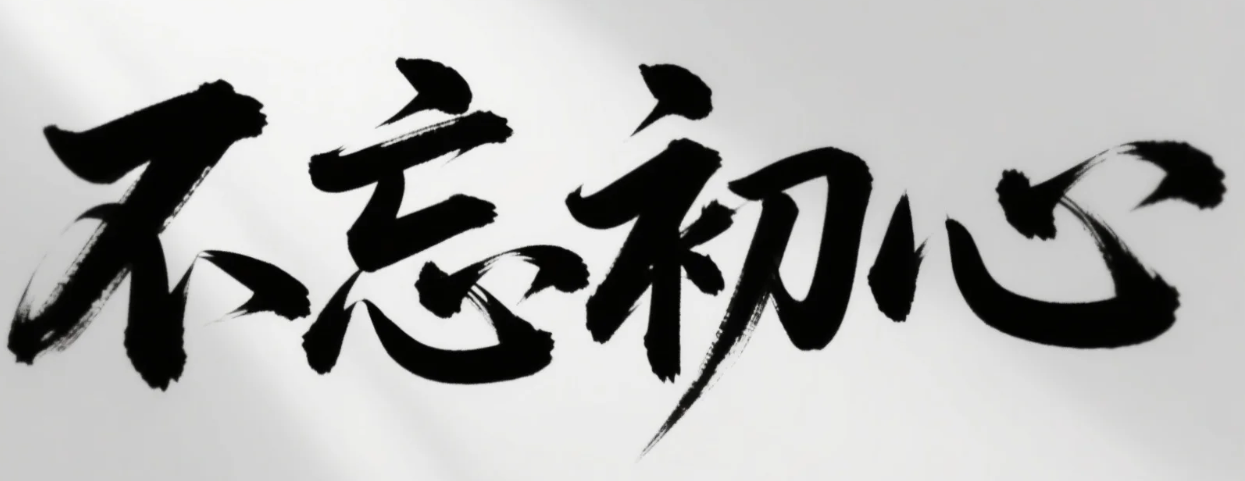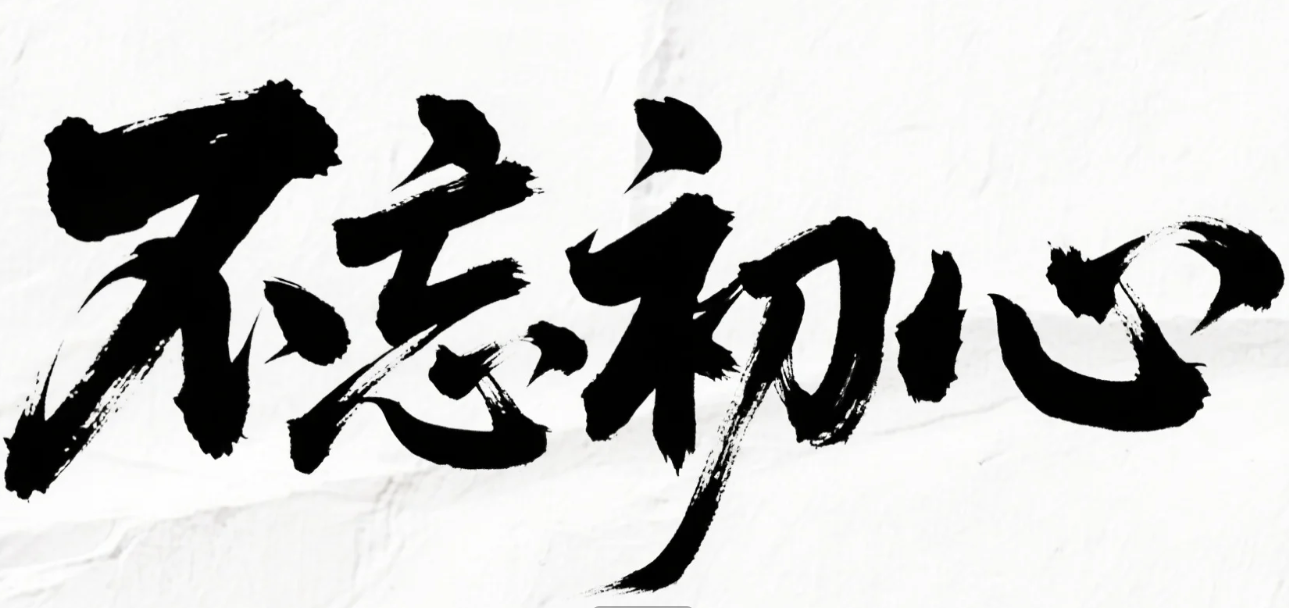
有了AI字体设计变的简单起来
AI可以直接设计字体,以前想都不敢想,如今ai已经很成熟的设计字体了。抓紧利用起来吧。
不用太多提示词,直接说生成毛笔字,最多加点特点词,可以根据需求加上,比如笔触、飞白、豪放、
毛笔字
钢笔字
立体字
后面还有一些,不再分类了,有毛笔字体、粉笔字体、哥特字体、立体字体等。